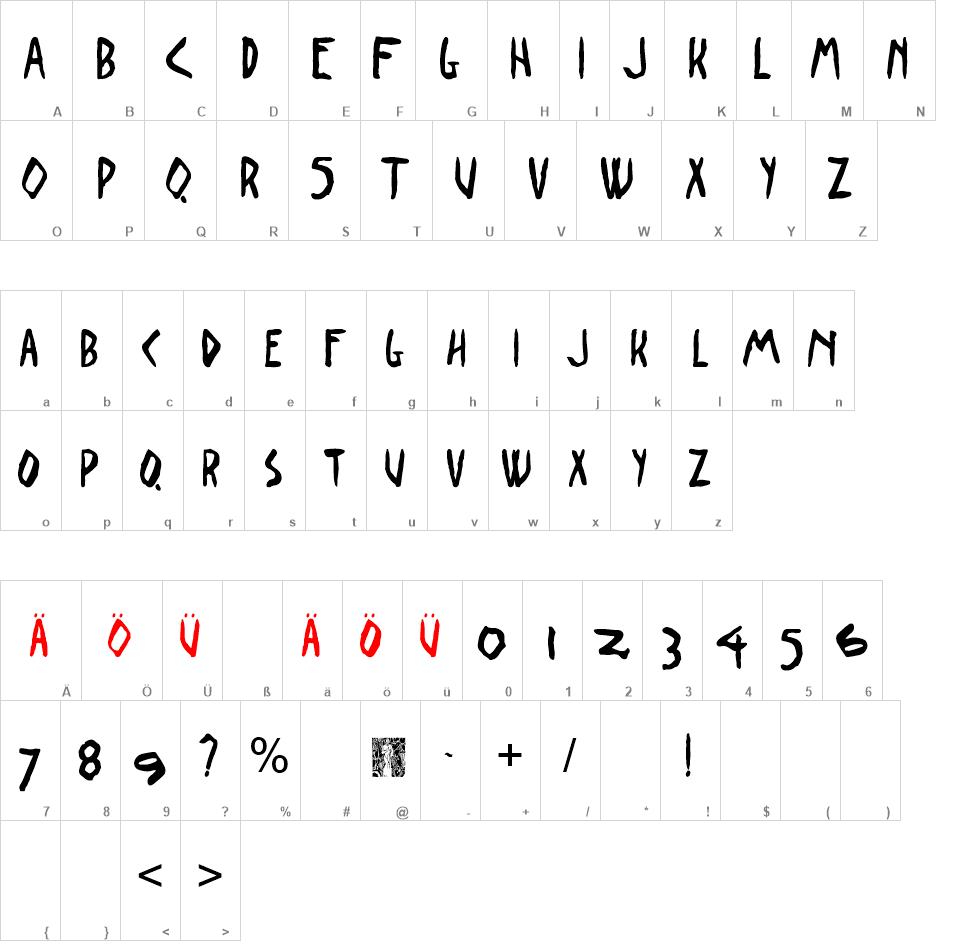
Paulistana 1922
Série Paulistana – Pesquisa sobre a tipografia na arte, na arquitetura e nos documentos da cidade de São Paulo (Brasil).
Paulistana 1922 é baseada no catálogo elaborado por Di Cavalcanti para a Semana de Arte Moderna ou Semana de 22, entre 11 a 17 de fevereiro de 1922, no Teatro Municipal da cidade de São Paulo.
Paulistana series - Research about the typography in the art, the architecture and documents of São Paulo city (Brazil).
Paulistana 1922 is based on the catalogue elaborated by Di Cavalcanti for the Week of Modern Art or Week of 22, enters 11 to 17 of February of 1922, in the Municipal Theater of the city of São Paulo.